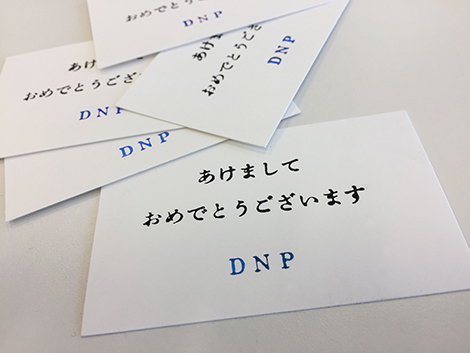
第40回 2017年も秀英体で年賀状を作ろう!
はやいもので今年も師走です。
新しい年のご挨拶、年賀状に秀英体はいかがでしょうか。
これまで1年のご愛顧に感謝の気持ちを込めてお届けしてきた「秀英体で年賀状」も2005年にスタートして干支がひと回り、年末恒例のコネタとなりました。
今回は、DLmarketにて販売中の秀英体フォントや『大人の科学マガジン 小さな活版印刷機』で刷ることができる秀英体と組み合わせるのにぴったりなイラストをLINEスタンプ「レトロな活版印刷 秀英体見本帳」から、お届けします。 昨年好評だった、そのまま使えるテンプレートも準備しました。
2018年の干支は「戌」です!
まずは戌のイラストから……
秀英アンチック
(漢字:秀英角ゴシック金B)
秀英四号かな
秀英四号太かな
(漢字:秀英初号明朝)
おめでたいイラストとともに……
秀英にじみ明朝L
フォントであれば、文字のサイズも色も自由自在。「戌」の文字をメインにして、こんなカラフルな年賀状も作ることができます。
「大人の科学マガジン 小さな活版印刷機」のふろくで刷ると、「あけましておめでとう」の文字も、こんな印象になります。
2017年はより多くの方に秀英体フォントをお使いいただけるよう、フォントワークスLETS、Adobe Typekitへの搭載、DLmarketでのダウンロード販売などをスタートし、ご提供の幅がぐっと広がった1年でした。
また、映像で「秀英体」と「活版印刷の職人」のご紹介をはじめた年でもあります。秀英体が使われている出版物といえば、広辞苑。広辞苑は、初版から年明けに発売を控える第七版まで、すべて秀英体です。映像の本篇では、秀英体が使われ続ける理由を岩波書店の平木さんにコメントいただきました。
さらに今年は、「秀英にじみ明朝L」をMORISAWA PASSPORTユーザーの皆さまのお手元に届けることもできました。さっそく書籍や雑誌などでご利用いただき、感謝の気持ちでいっぱいです。目下、「秀英にじみ丸ゴシックB」を開発中です。リリースを楽しみにお待ち下さい!